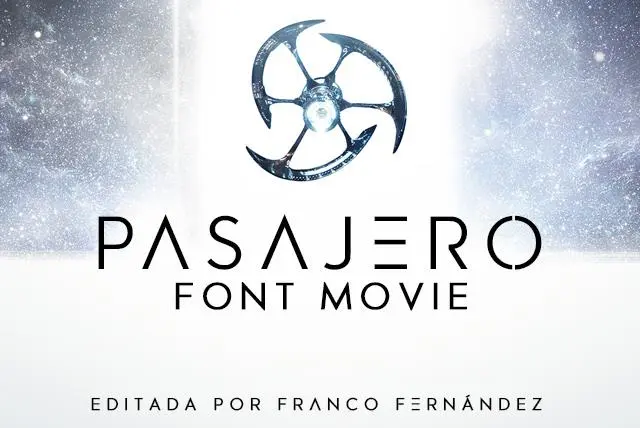
A Pasajero Font é uma tipografia sans-serif criada pelo designer espanhol Franco Fernández que se destaca por sua simplicidade e elegância moderna. Se você está procurando uma fonte versátil para trabalhos comerciais, este é o alvo perfeito. Ela combina bem com diversos estilos de design, desde sites profissionais até logotipos de filmes e viagens. Em 2017, Franco lançou esta font no seu blog oficial FontMovie, sugerindo que quem deseja usar sua tipografia comercialmente faça um depósito em sua página. A Pasajero Font não só oferece uma aparência clara e fácil de ler, mas também tem um design minimalista que se adapta perfeitamente à cultura cinematográfica e ao mundo da viagem.